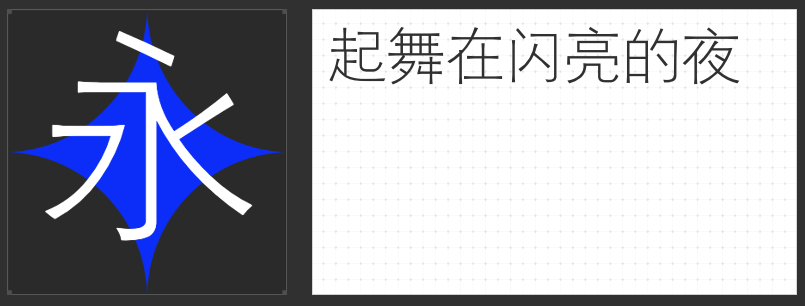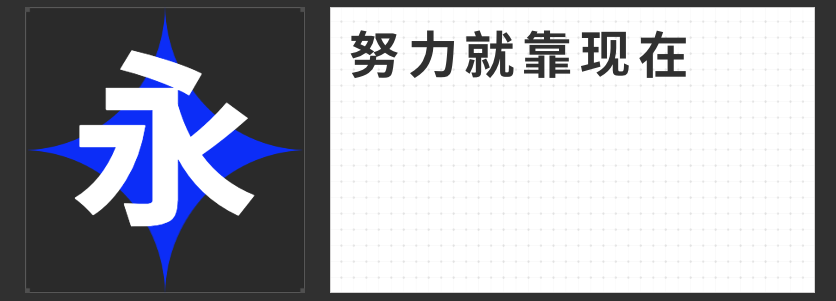
稳健如峰 永恒如墨——四款经典百搭黑体字库推荐
在追求视觉表现力的设计领域,黑体字始终占据不可替代的基石地位。它既是承载信息的容器,亦是构建版面的骨骼。今次甄选的这四款黑体字体,以纯粹理性之美诠释设计的永恒性,用无衬线的简洁线条搭建起跨越场景的百搭可能。
一、字圈也字时代黑体
这款字体凝结着工业时代的智慧密码。笔画末端的喇叭口造型,源自铅字印刷时期对工艺缺陷的巧妙转化——当油墨在金属字模边缘自然晕开,竟意外成就了装饰性与功能性并存的经典样式。数字时代的复刻保留了这份历史温度,方头方尾的笔画框架与微妙的端口弧线,让字体在规矩中透出灵动的呼吸感,尤其适合传统品牌升级或文化类设计项目。
二、励字细黑简
清瘦如竹的骨架展现出知识分子的理性气质。完全摒弃装饰性笔画的极简设计,使每个字符都成为精确的信息载体。字面正方形的严谨比例,确保在密集排版时仍能维持呼吸感;笔画粗细的绝对统一,则让长文阅读如同清风拂面。这款字体是学术著作、财经报告等严肃场景的不二之选。
三、励字超粗黑简繁
当黑体突破常规重量,便化作视觉重锤。这款字体的斜切笔画设计暗藏动态张力,横竖笔画的视觉等粗处理强化了力量感,方头方尾的硬朗造型在海报主标、品牌口号等场景极具穿透力。特别设计的简繁双版本,让传统文化与现代审美在粗壮笔画间达成微妙平衡。
四、励字励黑简
超常规的字重并未牺牲可读性,反而通过严谨的架构控制展现出黑体的终极形态。无字肩的简洁设计消除视觉干扰,方头起笔与绝对均匀的笔画宽度,使这款字体成为书刊标题的定海神针。在需要强调的视觉焦点,它能以不容置疑的稳重感锁定观众视线。
这四款黑体如同设计师的工具箱底层逻辑。它们剥离潮流的浮华表象,以近乎数学公式的严谨性,为设计世界搭建起永不褪色的视觉坐标系。